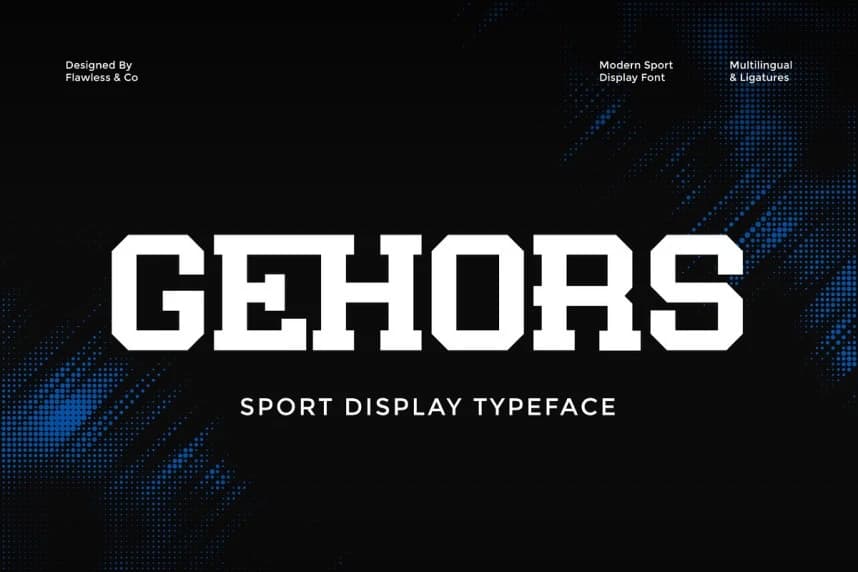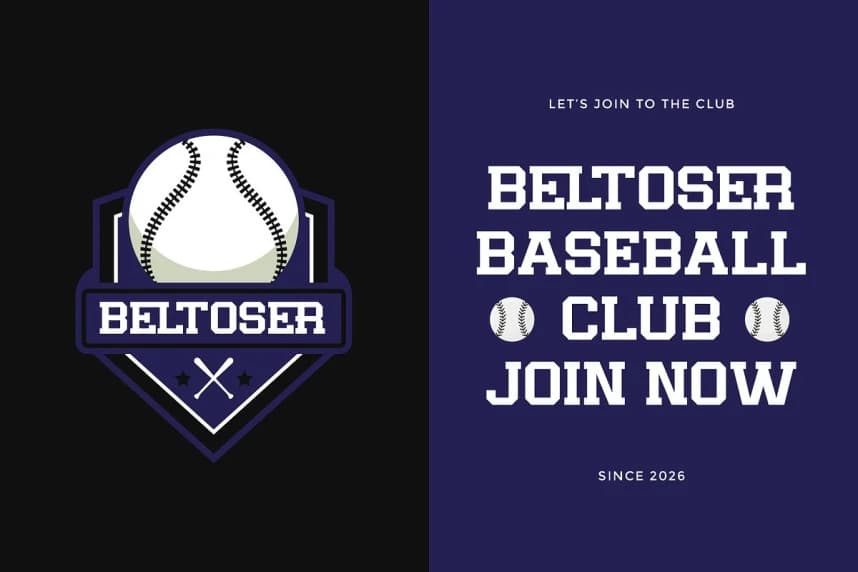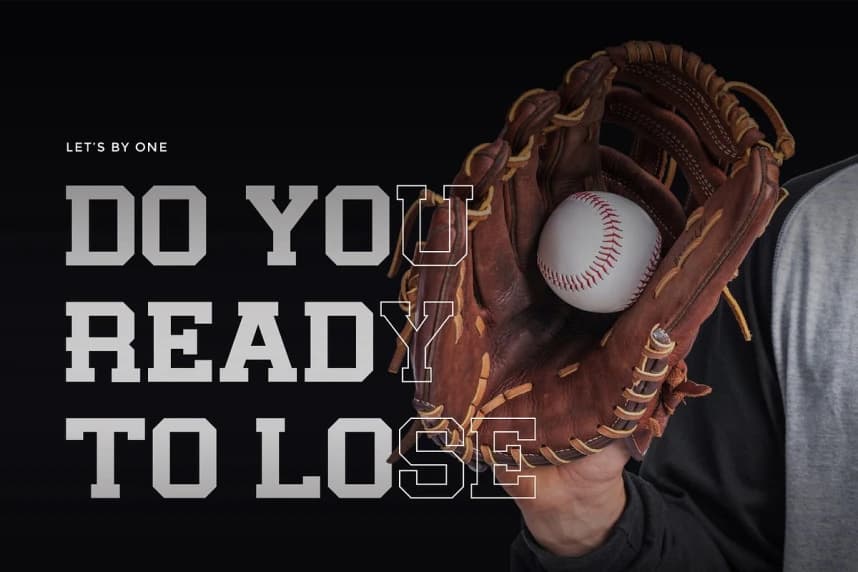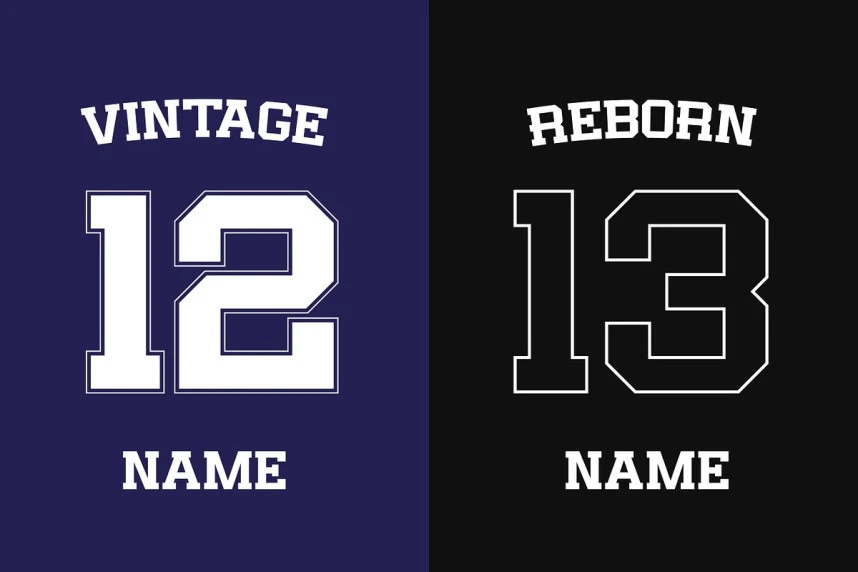
Gehors Font
Gehors Font, güç, hız, hassasiyet ve rekabetçi enerji ifade etmek üzere tasarlanmış modern bir spor gösteri yazı tipidir. Keskin açılar, cesur yapı, sıkı boşluklar ve ileri doğru hareket eden bir yapı ile Gehors, güçlü ve agresif bir hareket hissi yaratır.
Gehors Font, güç, hız, hassasiyet ve rekabetçi enerjiyi ifade etmek için tasarlanmış modern bir spor gösterim yazı tipidir. Keskin açılar, kalın yapı, sıkı boşluklar ve ileriye doğru hareket eden bir yapı ile Gehors, güçlü ve saldırgan bir hareket hissi yaratır.